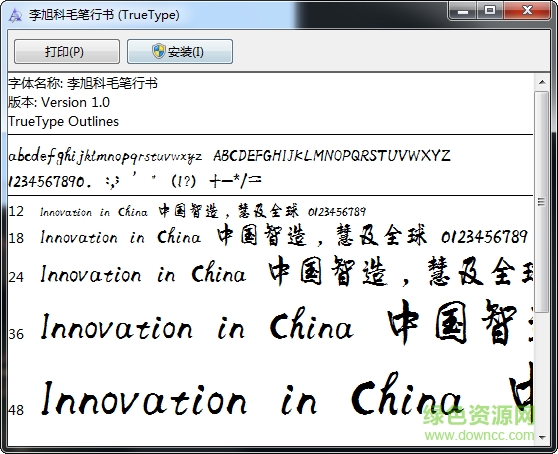
lixukexingshu regular字體是一款ttf格式的李旭科行書字體,筆觸和諧,筆勢(shì)迅捷,流暢灑脫,蒼勁多姿,藝術(shù)性與實(shí)用性兼具,需要的朋友快來(lái)綠色資源網(wǎng)下載吧!
行書是楷書的快寫,是楷書的流動(dòng)。經(jīng)過(guò)對(duì)幾組楷書與行書個(gè)字的分析,發(fā)現(xiàn)楷書與行書書寫時(shí),點(diǎn)畫的寫法,用筆需遵循的準(zhǔn)則,如中鋒,鋪毫,逆入平出,提按起主,藏鋒等都是一致的,只是行書書寫時(shí)比較舒展,流動(dòng)。